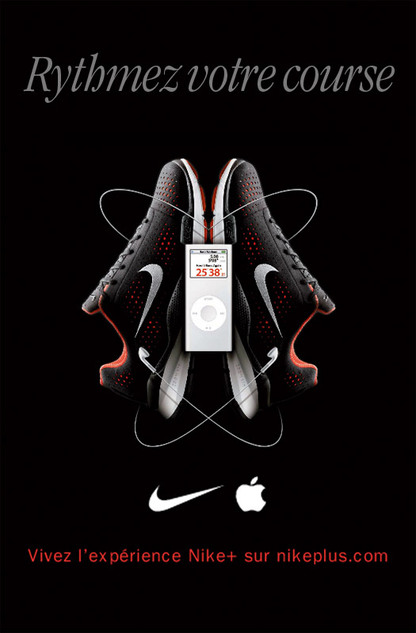
Hier je découvre la nouvelle pub de Nike associée à Apple (I-Pod). Excellente copy-stratégie. Bundle des plus astucieux concernant les 7 à 77 ans qui jogguent dans les allées des Buttes Chaumont à la rosée du matin. L’illustration? rien à redire. Un petit bijou d’arrangement entre les baskets et les fils des écouteurs parfaitement symétrisés, enroulant les nikes comme un cadeau à emporter. Noël n’est pas loin, c’est la saison des cadeaux. Pour ce qui est de la typo je suis plus perplexe. Ne dis rien de la base-line du bas sauf à la remonter un peu parce que trop loin, déconnectée de l’image des produits. Si j’avais été consulté, j’aurais dit d’associer plus l’image à voir, au texte à lire. Quant à la neutralité aveuglante de l’Helvetica en Noir au Blanc du texte supérieur, voici quelques propositions qui me semblent mieux adaptées pour délivrer un message plus en adéquation avec la nature du cadeau.
Voici d’abord la pub originale:
1 | un titre plus hype qui rappelle la technicité des deux produits qui bénéficient tous les deux d’investissements R&D considérables. Titre légèrement gris afin de laisser vivre la photo sans l’écraser.
2 | un titre plus hype qui rappelle aussi la
technicité des deux produits mais titrage plus élégant, typo linéale avec des arrondis plus doux, newage, gris aussi, afin de
mieux laisser vivre la photo.
3 | un titre plus dynamique parce qu’italique, la typo penche en avant comme la silhouette du coureur en plein action. Si vous analysez la sémantique-utilisateur des produits montrés, le texte qui parle de rythme, donc de la course, l’italique «porte» bien le message de même que la proposition ci-dessous:
4 | sauf que là j’ai joué avec un vieux code typo, celui du garamond itc light condensed italique, qui a été longtemps la typo fétiche d’Apple. Une manière de rappeler la marque à la pomme qui malgré tout est assez noyée au milieu de la paire de basket.
5 | là c’est mon choix personnel, je trouve que les mots devaient exprimer mieux le concept du rythme, de la musicalité hype and hop, du joggeur à la fois exigeant et geek d’une certaine way of life tourné vers l’avenir. La typo, à la fois forte et discrète par le jeu des gris participe pleinement à la puissance de l’offre de Nike et d’Apple.
Je ne dis pas que cette pub est mauvaise mais comme toujours, chaque fois que je regarde une pub, je me pose la question si on n’a pas négligé la dimension typographique d’un message. C’est le rôle d’un type director que de venir en bout de création valider et/ou proposer des solutions qui véhiculent mieux un message, qui s’associe mieux à la stratégie d’une offre.
Qu’en pensez-vous?